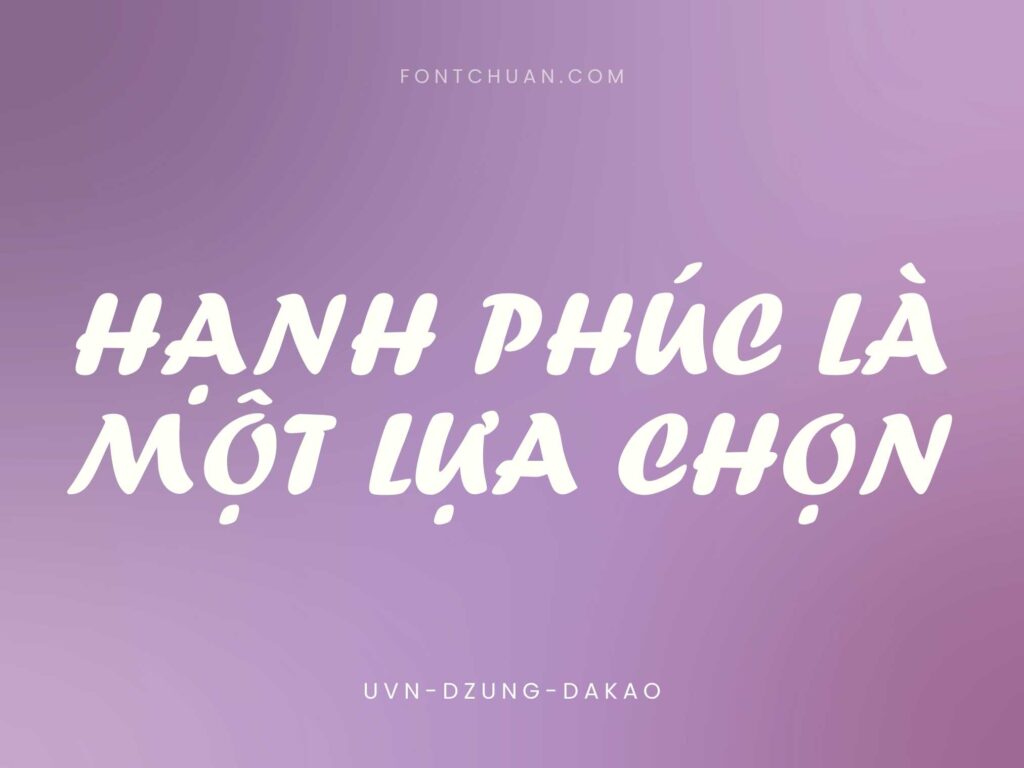
Font UVN Dzungdakao Việt Hóa
UVN Dzung Dakao là một phông chữ script mang phong cách viết tay đậm nét, tạo cảm giác năng động và thanh lịch. Các ký tự được thiết kế với độ nghiêng nhẹ, mang lại sự uyển chuyển và tinh tế cho văn bản. Phông chữ này hỗ trợ đầy đủ các ký tự tiếng Việt, giúp người dùng dễ dàng sử dụng trong các dự án sáng tạo liên quan đến văn hóa Việt Nam.
Với thiết kế độc đáo và nghệ thuật, UVN Dzung Dakao phù hợp cho các ứng dụng như thiệp mời, tiêu đề sách, thiết kế logo và các ấn phẩm nghệ thuật. Trong lĩnh vực sự kiện, phông chữ này có thể được sử dụng trong các dịp như lễ hội, lễ cưới và các sự kiện văn hóa. Bên cạnh đó, UVN Dzung Dakao cũng là một Font chữ ảnh cưới lý tưởng, giúp trang trí album ảnh cưới, thiệp cưới và các sản phẩm kỷ niệm, mang đến không khí lãng mạn, tinh tế và nghệ thuật cho các thiết kế. Ngoài ra, font này cũng phù hợp với các ngành nghề như thiết kế đồ họa, nghệ thuật trang trí và xuất bản.